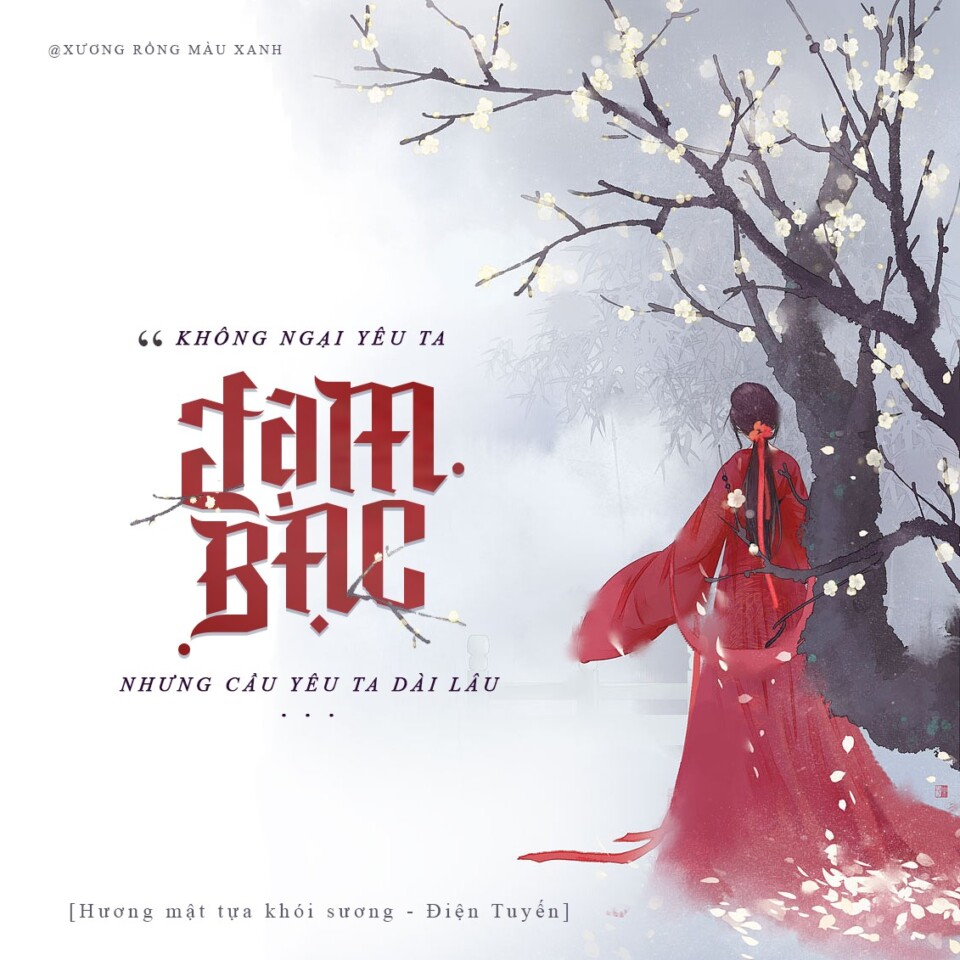
Font Việt hóa MTD Black Baron Gothic – Bộ Font Đẳng Cấp Cho Thiết Kế Việt
Giới thiệu về Font Việt hóa MTD Black Baron Gothic
Trong thế giới đồ họa hiện đại, việc tìm kiếm một Font Chữ vừa mang nét cổ điển vừa giữ được sự sang trọng là điều không hề dễ dàng. Font Việt hóa MTD Black Baron Gothic chính là giải pháp hoàn hảo cho những nhà sáng tạo đang tìm kiếm sự khác biệt. Đây là một bộ phông chữ thuộc phong cách Gothic nhưng đã được tinh chỉnh để mang lại cảm giác dễ đọc và thân thiện hơn. Với sự tỉ mỉ trong quá trình Việt hóa của đội ngũ MTD, bộ font này đã khắc phục hoàn toàn lỗi hiển thị dấu tiếng Việt, giúp các văn bản trở nên chỉn chu và chuyên nghiệp tuyệt đối.
Những đặc điểm nổi bật của Font Việt hóa MTD Black Baron Gothic
Thiết kế độc đáo và mạnh mẽ
Font Việt hóa MTD Black Baron Gothic sở hữu những đường nét dày dặn, dứt khoát nhưng không kém phần uyển chuyển. Cấu trúc chữ cái được xây dựng dựa trên cảm hứng từ các bản in cổ thế kỷ trước, tạo nên một sức hút thị giác cực kỳ mạnh mẽ. Điều này giúp bộ font trở nên lý tưởng cho các thiết kế tiêu đề sách, bìa tạp chí hoặc các biểu trưng thương hiệu đòi hỏi sự quyền lực và tinh tế.
Tính ứng dụng cao trong học tập và công việc
Cách sử dụng và kết luận